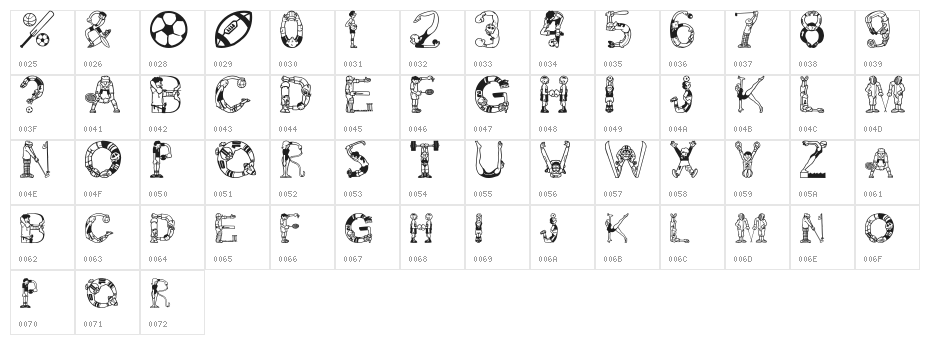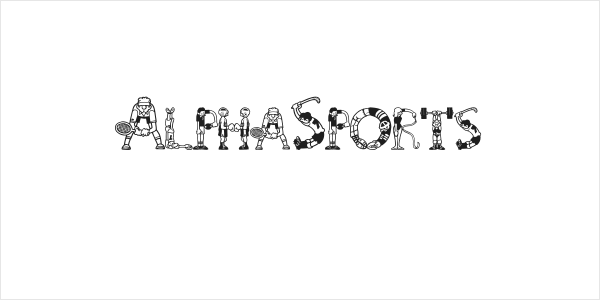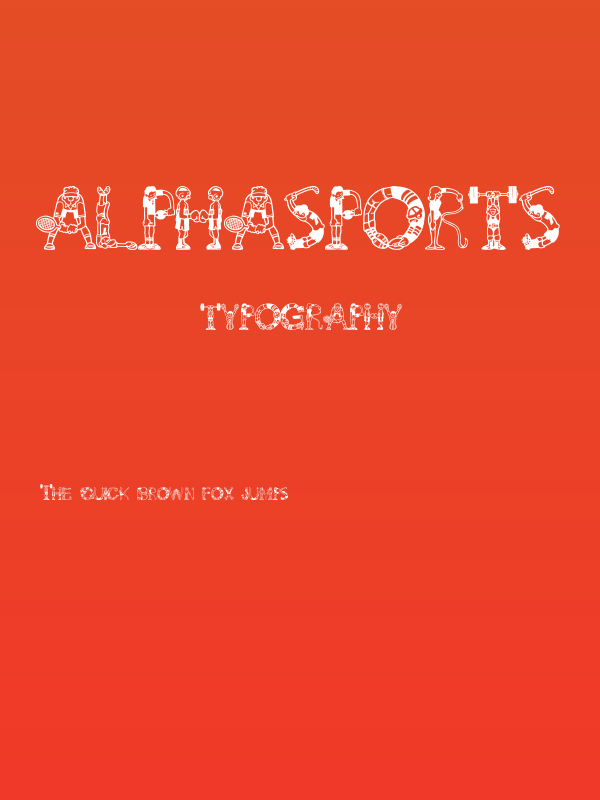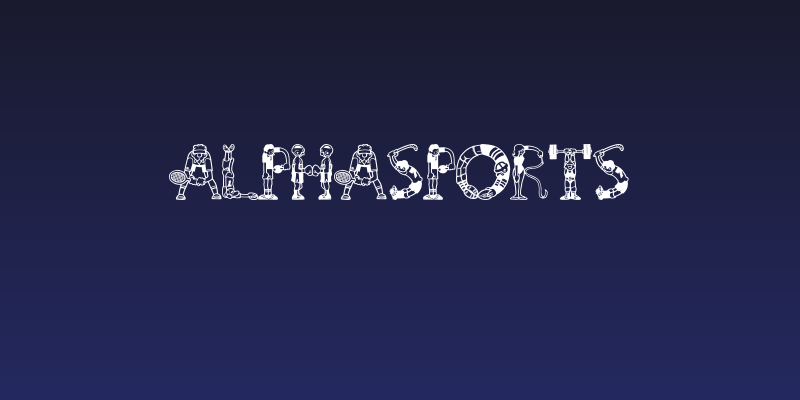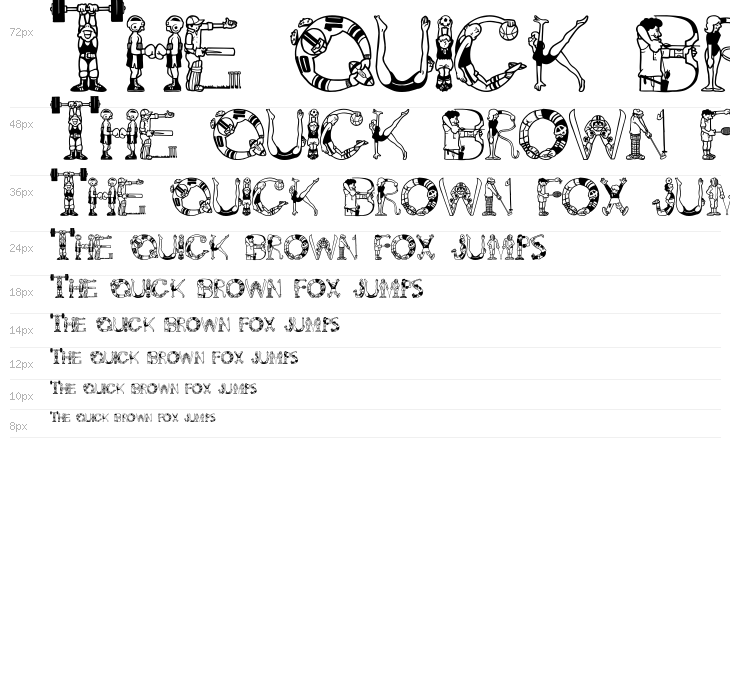
AlphaSports Font
| Stil general | Playful, Thematic, Energetic |
| Caz de utilizare | Logos, Headlines, Posters, Educational Materials |
| Proiecte propuse | Ideal for sports branding, event promotions, educational materials, and playful designs. |